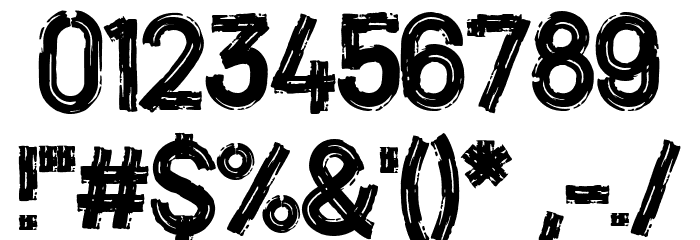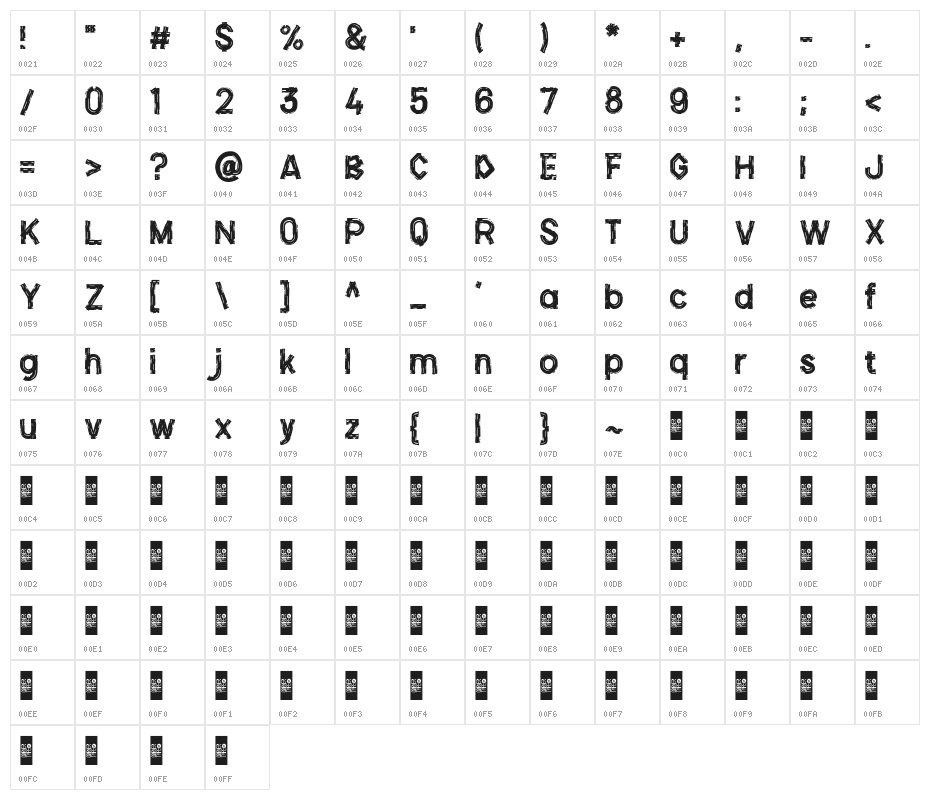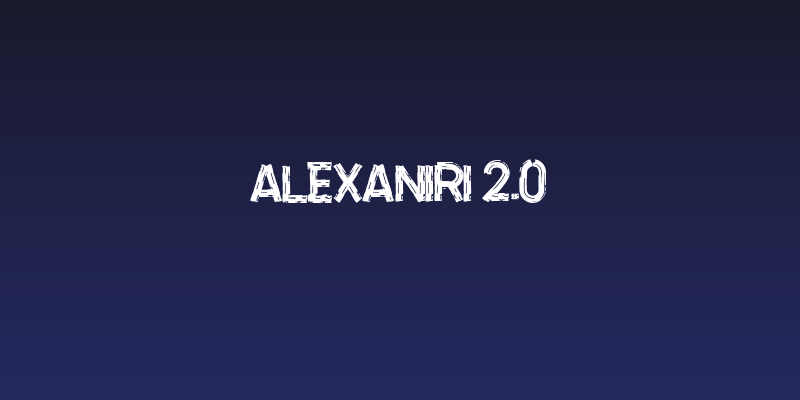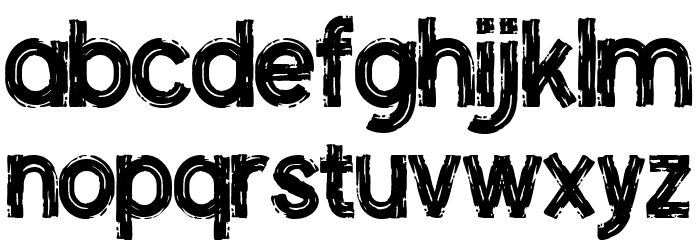
Alexaniri 2.0 Font
✎ Messy
| Proiecte propuse | Ideal for posters, album covers, streetwear branding, or any project needing a grunge or urban aesthetic. |